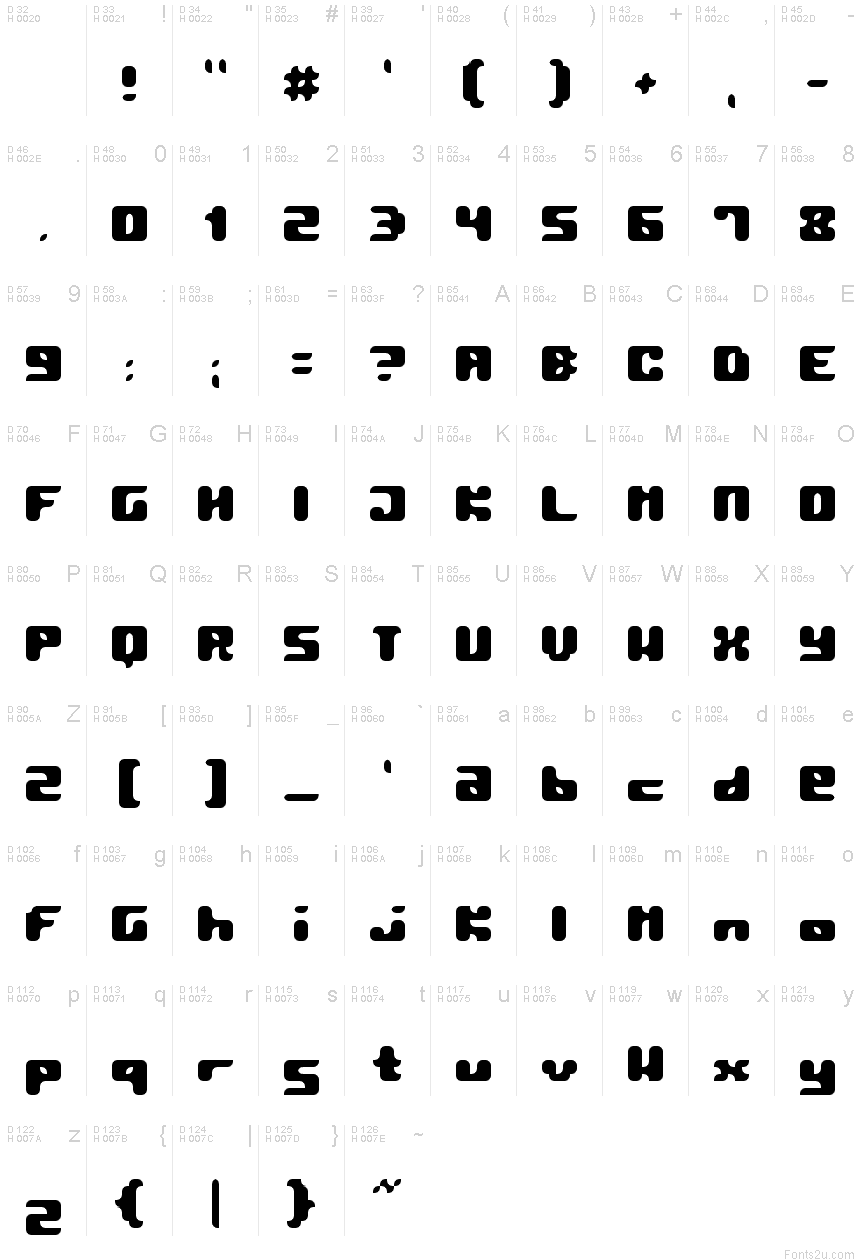
Pormask 2039 od TarmSaft Font Factory to darmowy, futurystyczny krój display o masywnej sylwetce w stylu sci-fi. Litery wyglądają jak odlane z miękkich, prostokątnych bloków, z głęboko zaokrąglonymi narożnikami i wycięciami w kształcie łezek, dzięki czemu alfabet jest bardziej zabawny niż surowy.
To połączenie sprawia, że naturalnie odnajduje się w plakatach retro sci-fi, oprawie muzyki elektronicznej, brandingu gier arcade, opakowaniach zabawek czy planszach tytułowych, gdzie potrzebna jest wyrazista grafika. Jako darmowy font, świetnie sprawdzi się również w logotypach, na okładkach i w krótkich nagłówkach, które wykorzystują jego pękate formy i małe wewnętrzne kropelki dla dodania charakteru.
Pormask 2039